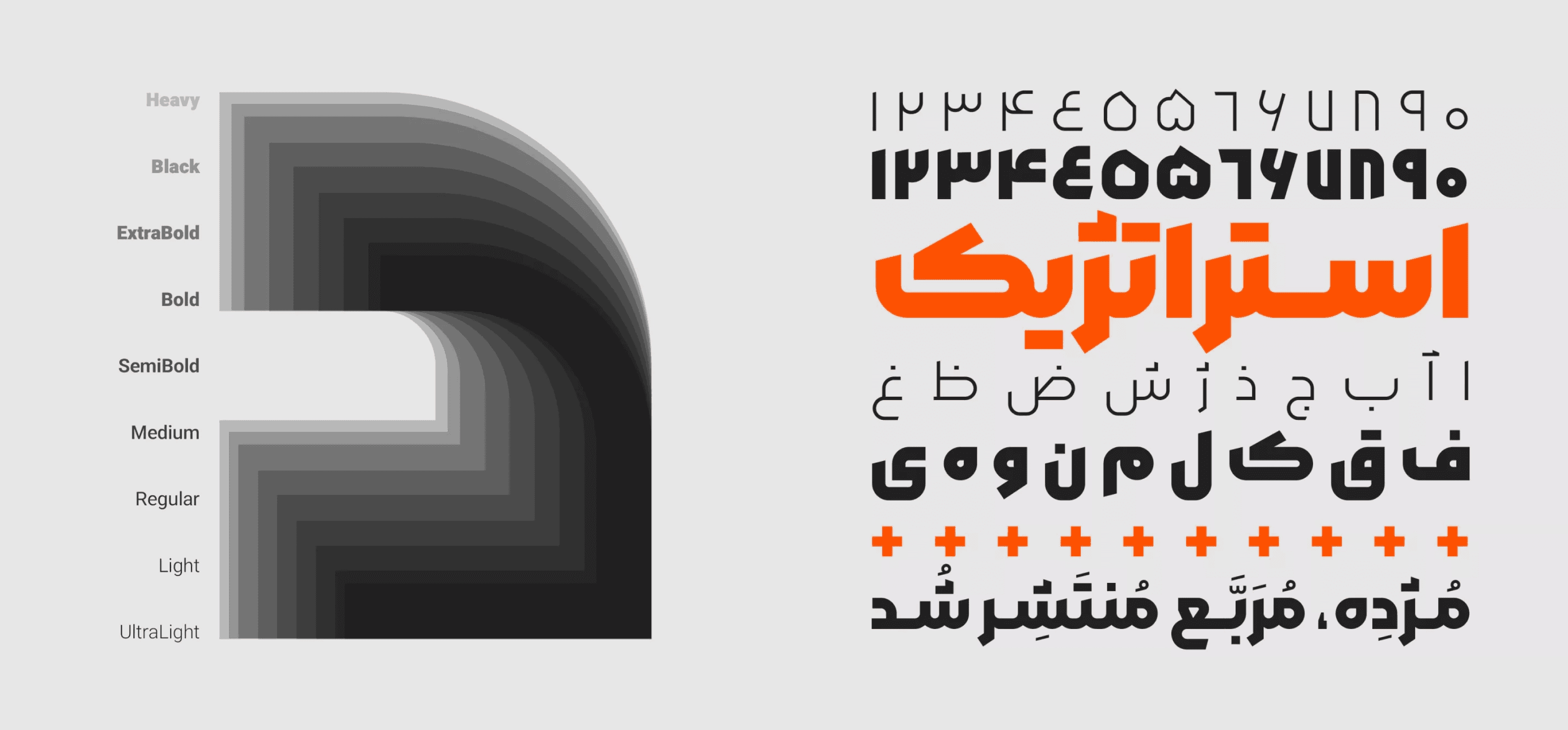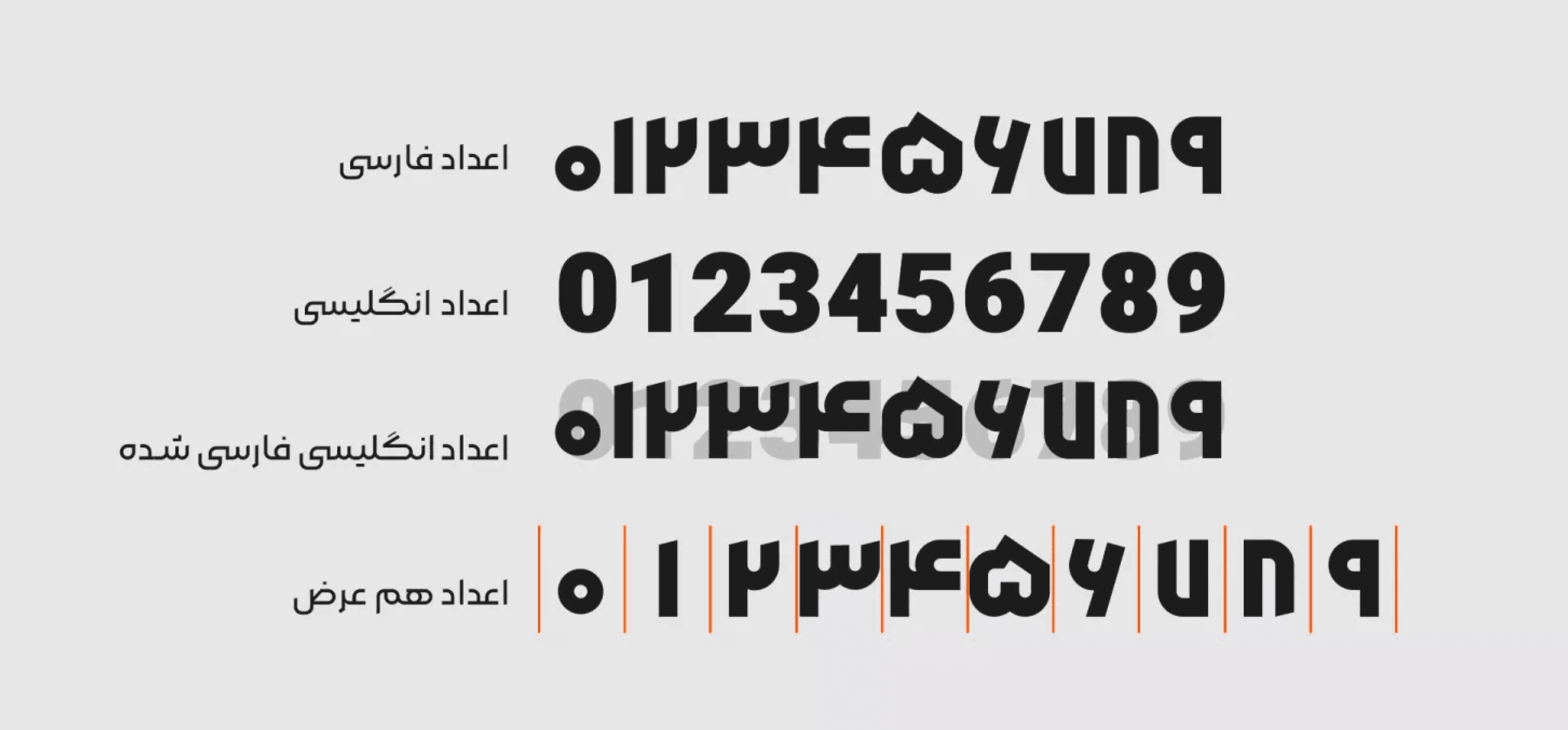
خط Morabba هو خط هندسي مستوحى من خط الكوفي البنّائي.
صُمم Morabba ليتناسب مع الكلمات والعبارات القصيرة، ويُعد مثاليًا للمواضيع الحديثة والتجارية، مثل الشعارات النصية، والعروض التقديمية، وأغلفة وسائل التواصل الاجتماعي، والإعلانات، وتصاميم التغليف.
خط Morabba هو خط هندسي مستوحى من خط الكوفي البنّائي.
صُمم Morabba ليتناسب مع الكلمات والعبارات القصيرة، ويُعد مثاليًا للمواضيع الحديثة والتجارية، مثل الشعارات النصية، والعروض التقديمية، وأغلفة وسائل التواصل الاجتماعي، والإعلانات، وتصاميم التغليف.
خط Morabba هو خط هندسي مستوحى من خط الكوفي البنّائي.
صُمم Morabba ليتناسب مع الكلمات والعبارات القصيرة، ويُعد مثاليًا للمواضيع الحديثة والتجارية، مثل الشعارات النصية، والعروض التقديمية، وأغلفة وسائل التواصل الاجتماعي، والإعلانات، وتصاميم التغليف.